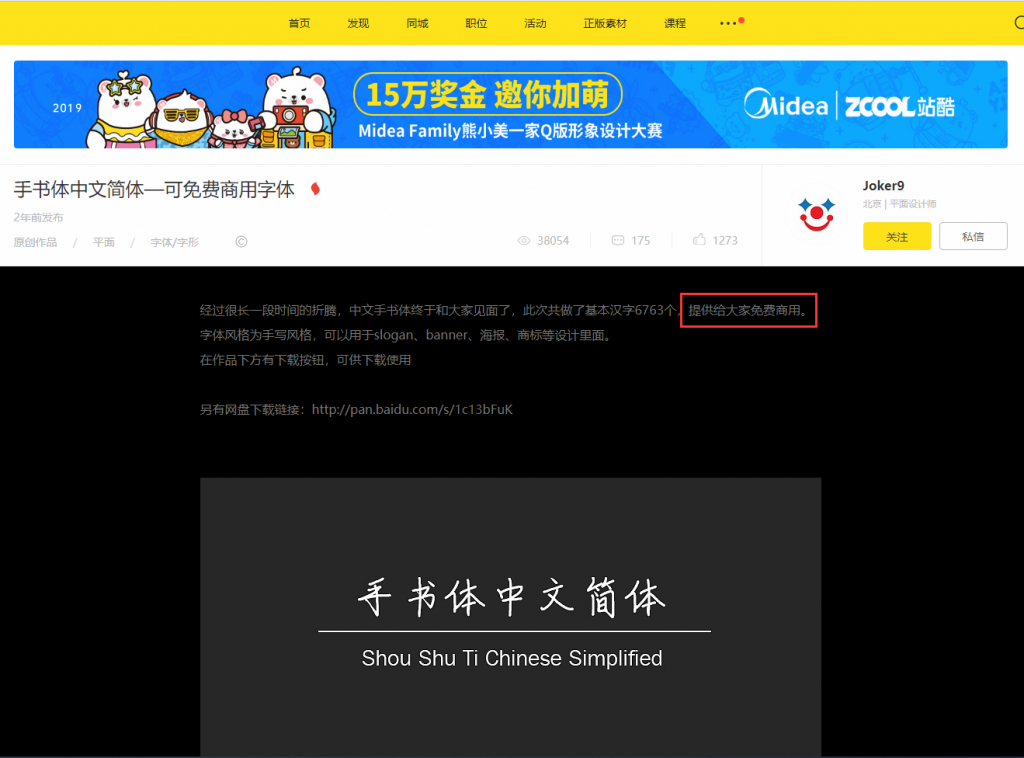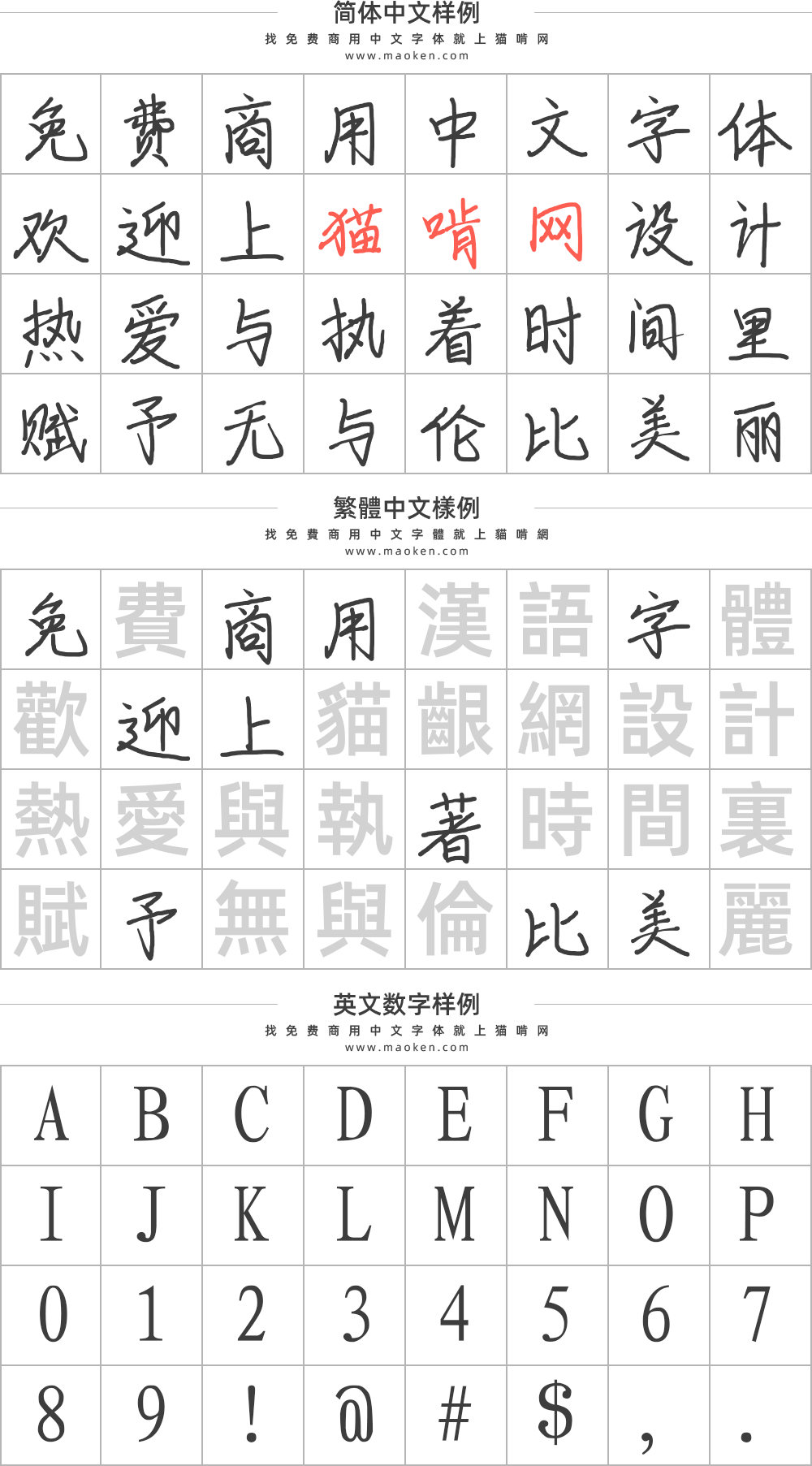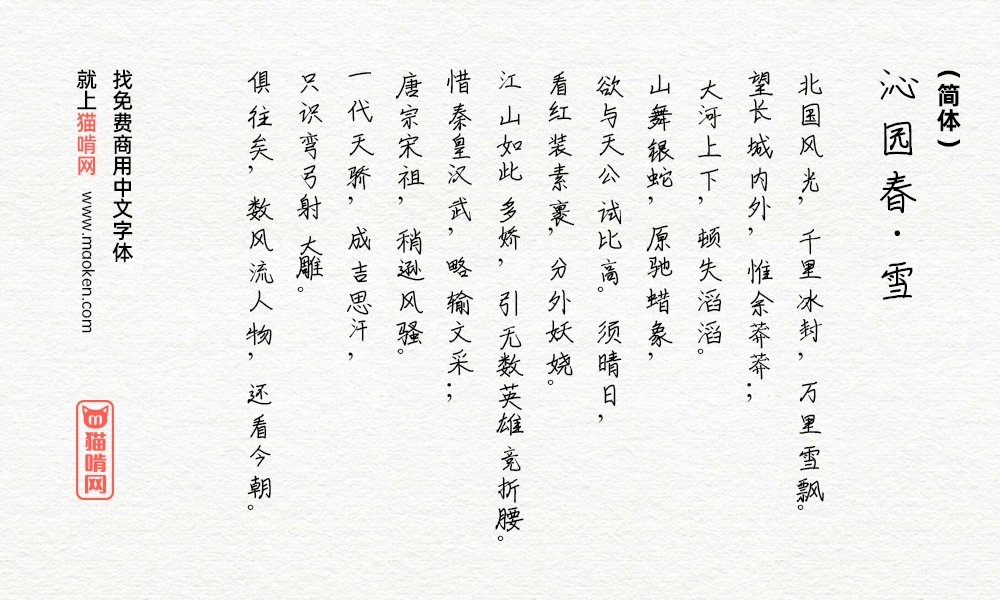
智勇手书体:一款非常漂亮的免费商用钢笔手写字体
字体作者:Joker9 (中国大陆) 字体字重:1个
字体作者:贾智勇(中国大陆) 字体字重:1个
智勇手书体是设计师Joker(站酷ID:Joker9)手写并制作分享给大家使用的字体。这款字体的名称在很多网站上都称为《手书体》,因为这款字体作者的名字叫贾智勇,所以猫啃网把这款字体称为智勇手书体。这款字体按照GB2312标准, 共做了基本汉字6763个 。这款字体风格为手写风格,可以用于slogan、banner、海报、商标等设计里面。这款手写字体字型十分漂亮,强烈推荐。